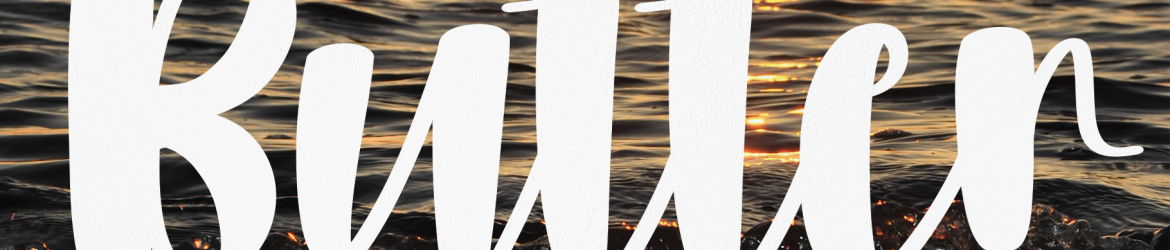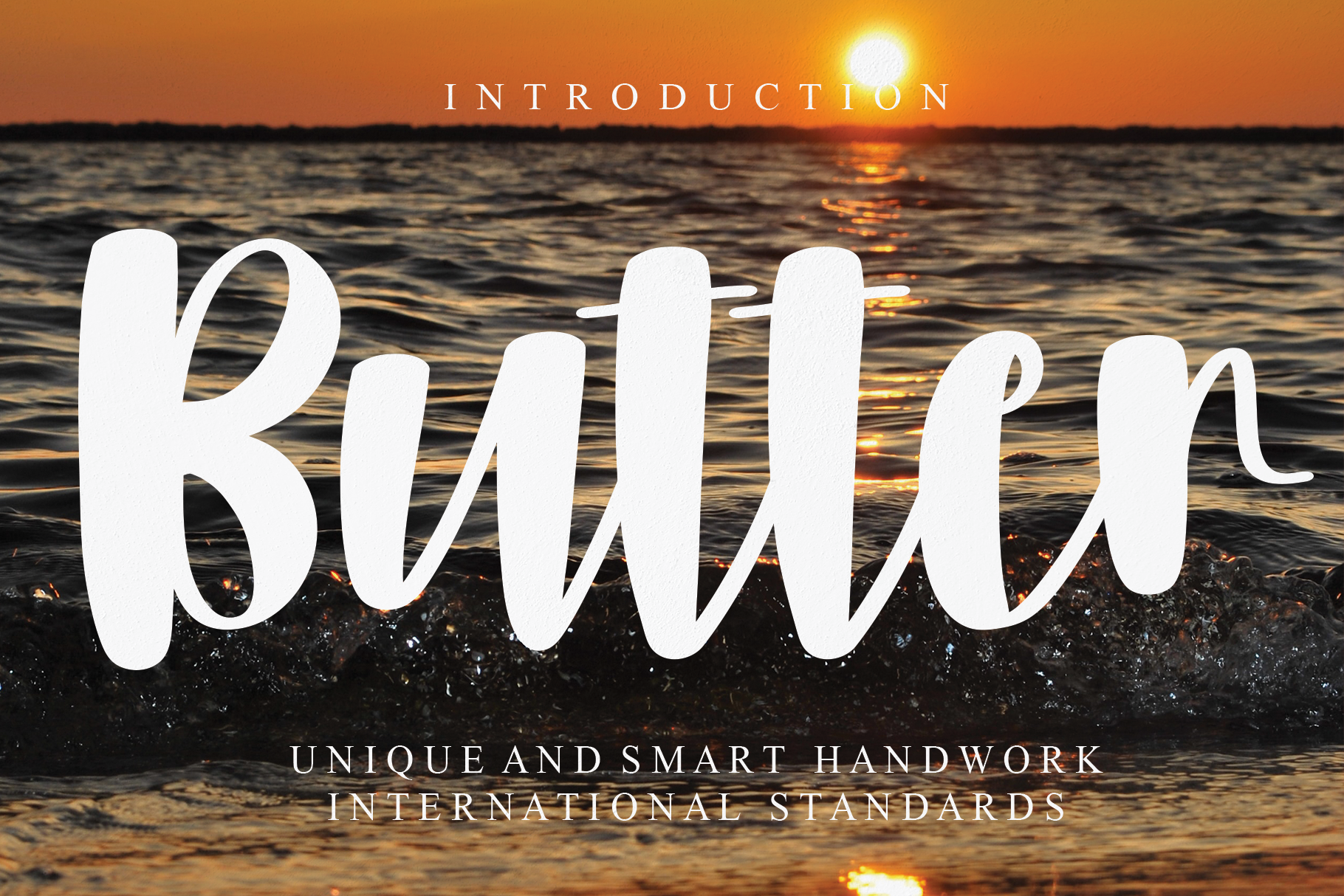
Butter Font – Fonte Grátis
Butter Font
Esta é uma fonte escrita à mão com estilo elegante e descontraído. Independentemente do assunto, esta fonte se tornará um belo recurso para seu acervo de fóntes, adicionando um toque refinado a qualquer criação. Acredo que você encontrará em Butters Font uma maneira única de decorar textos com autenticidade e sofisticação. Esta opção handwritten é perfeita para adicionar um quê de originalidade à sua identidade visual, seja no design gráfico, no branding ou na ilustração. Engajue-se nessa fonte versátil criada por CreativeLetter.